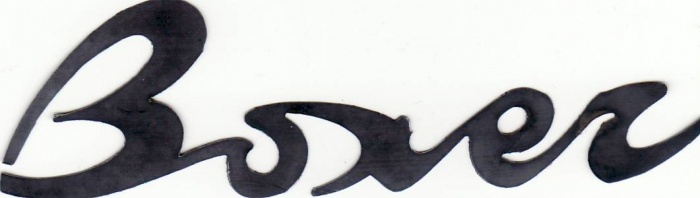
Suche Schriftart zu diesem Logo
Ich suche zu diesem Logo (Italien, Anfang der siebziger Jahre) passenden Schrifttyp.
Es besteht die Möglichkeit, das es sich hierbei um eigenständiges Werk handelt, welches nicht auf Basis eines Fonts entstanden ist.
Mit der Vermutung liegst du richtig. Das ist keine Satzschrift aus den 70ern, sondern als Schriftzug gezeichnet worden ...
Passend dazu? Ne schöne Groteske (Sans), je nach Geschmack ... kommt ja auch drauf an, was im Text steht und wieviel ... Eigentlich geht fast alles andere auch, solange es keine Schreib- oder Kursivschrift ist.
Ich würde vermutlich die https://www.myfonts.com/fonts/canadatype/semplicita-pro/ nehmen ...